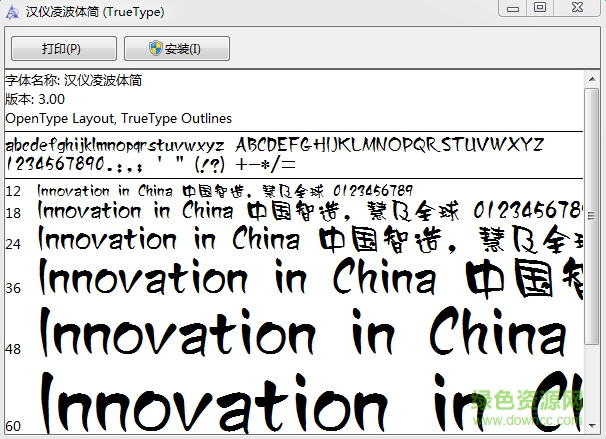
hyr1gj字體是一款充滿著趣味性的漢儀字體,筆畫看似隨意,但是整體看上去就會(huì)顯得很可愛(ài),適合需要用到各種藝術(shù)字體的朋友進(jìn)行創(chuàng)作,喜歡可以下載使用!
hyr1gj字體是漢儀字庫(kù)中的漢儀凌波體簡(jiǎn),是一款字形非常奇特的黑體字體,整體看上去往左進(jìn)行了傾斜,并且上方普遍比下方要寬,非常的有特色!